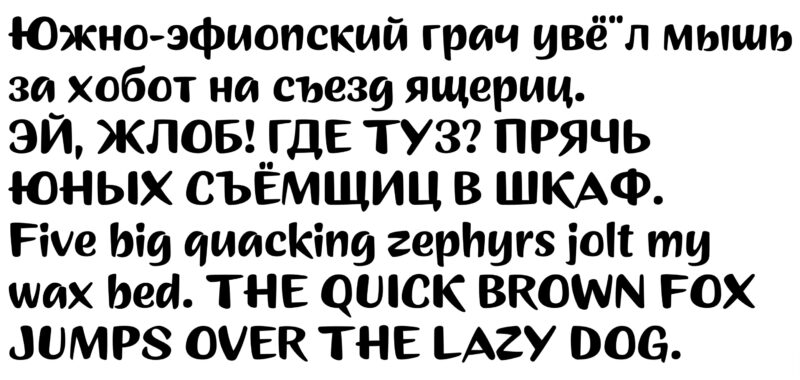
Идея этого шрифта пришла ко мне давным-давно. Но я все не решался взяться. И вот вчера (9.07.2026) внезапно взялся и сделал большую часть прописных.
А там и строчные сделались.
Первая версия этих букв появилась в этой музцитате. Они и перекочевали в Фонтлаб. Остальные дорисовал.
Забавно, что сто лет назад (где-то в 2004-м) у меня был подобный (как мне кажется) шрифт с таким же названием. Я его делал как модульный шрифт, из запчастей.
18.07.2026 – Между делом сделал узкую версию. Пара движений пальцами, но даже автоматическая версия смотрится отлично.
20.07.2026 – Баловство.